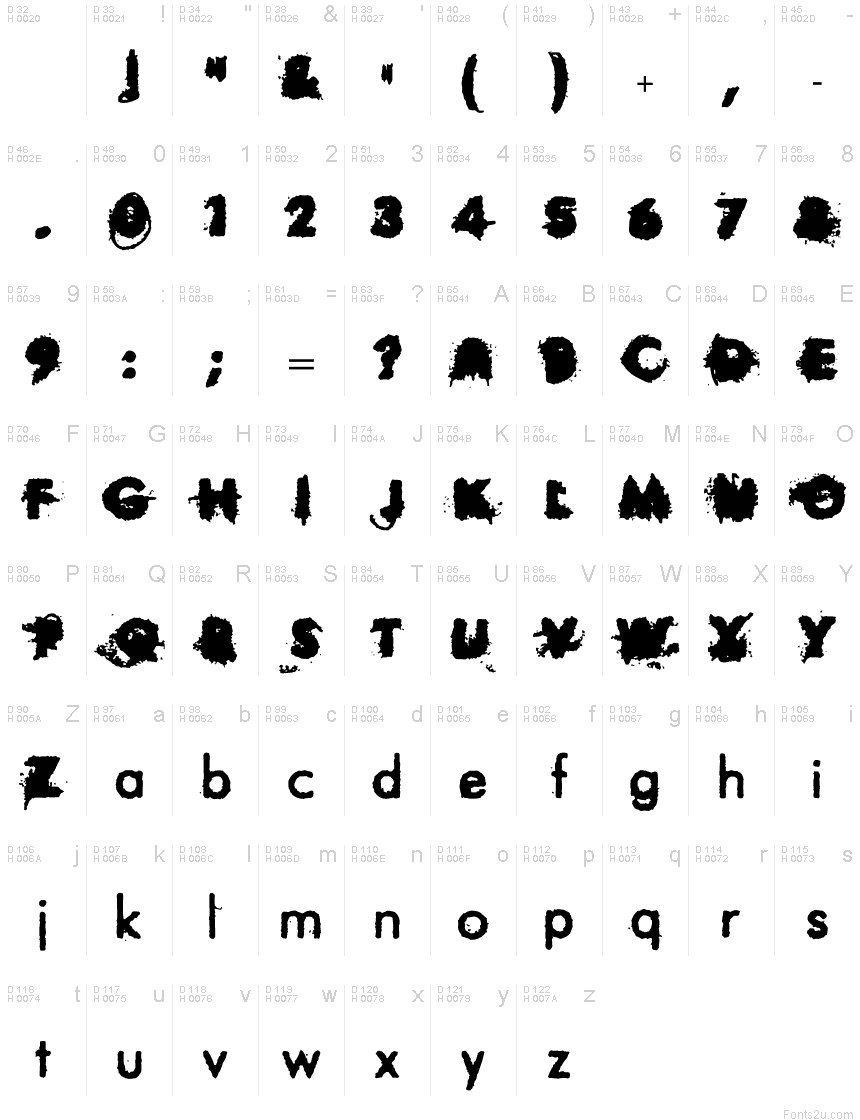
خط City Contrasts هو خط عرضي (Display) مجاني يتميز بطابع مشوه. تبدو أشكاله السميكة والمستديرة وكأنها تلطخت ببقع الحبر وأوساخ الشوارع، مما يترك حواف خشنة وغير منتظمة تضفي لمسة جريئة وحضرية. ورغم ذلك، تحافظ الحروف على تماسكها، مما يجعل هذا المظهر الفوضوي مقروءاً بوضوح، تماماً مثل رسومات الغرافيتي التي تسيل على جدار خرساني.
يتألق هذا الخط المجاني في ملصقات الحفلات، وعناوين أفلام الرعب، ومنشورات الفعاليات المستقلة، والمجلات، وأغلفة الألبومات، وتصاميم وسائل التواصل الاجتماعي ذات الطابع القوي. استخدم City Contrasts بأحجام كبيرة لتسمح للقوام المتناثر بأن يبرز بشكل كامل؛ وللحصول على أفضل نتيجة، ادمجه مع خط بلا زوائد (sans serif) محايد وبسيط للنصوص التكميلية لضمان بقاء الرسالة حادة وواضحة.
City Contrasts